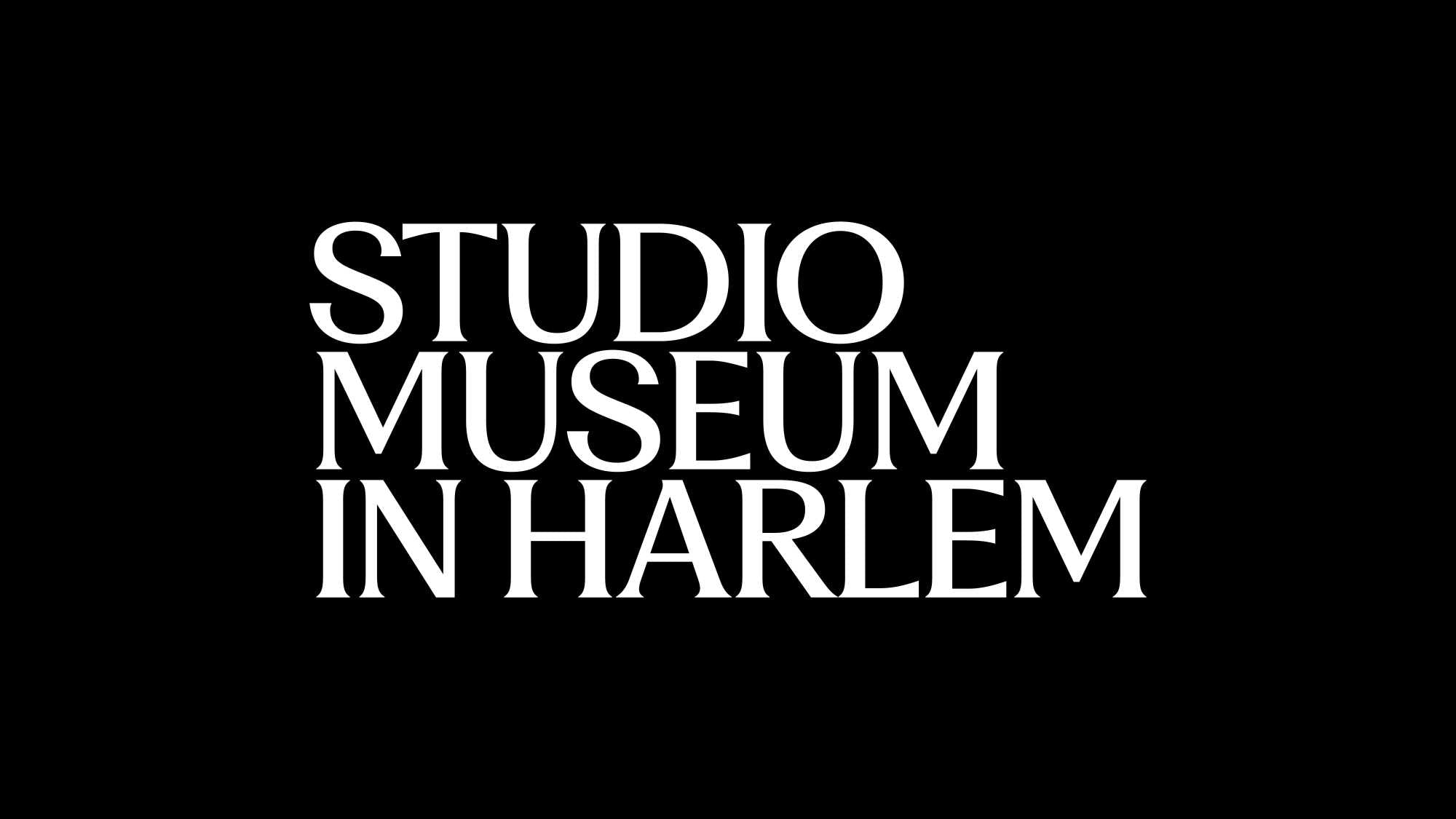
Une nouvelle image de marque pour le Studio Museum de Harlem. Alors que le s'apprête à ouvrir son premier espace dédié sur la 125e rue à Harlem, il s'est associé à Pacific pour repenser une image de marque qui perpétue un héritage d'innovation graphique.
Depuis sa création en 1968, l'identité du Studio Museum de Harlem a été définie par son engagement à créer un espace pour les artistes d'origine africaine.
Nous avons développé un positionnement et une stratégie de marque centrés sur trois piliers fondamentaux, inspirés du nom du : la raison d'être, le lien et le lieu. Le est une marque multiforme, animée par un objectif précis : défendre, étudier et préserver l'expression artistique noire (Studio) ; fédérer une communauté culturelle internationale () ; et créer un lieu qui met en lumière le quartier chargé d'histoire (Harlem).
Le nouveau logo est vertical, ce qui facilite son adaptation et son redimensionnement aux formats papier et numérique. L'empilement visuel des mots rend hommage à l'architecture de Harlem, les niveaux formant un perron, un élément emblématique du quartier et une référence à un élément de design du nouveau bâtiment du .
La nouvelle police de caractères de la marque (adaptée à partir de Fragment de Pangram Foundry) s'appelle « Studio Museum Black ». Raffinée et intemporelle, la Studio Museum Black a été choisie pour son élégance et son côté pratique. S'écartant de la dénomination conventionnelle des graisses, où « noir » désigne les graisses les plus épaisses et les plus grasses, la Studio Museum Black est principalement utilisée en graisse moyenne, défiant ainsi les attentes quant à la nature d'une police noire.